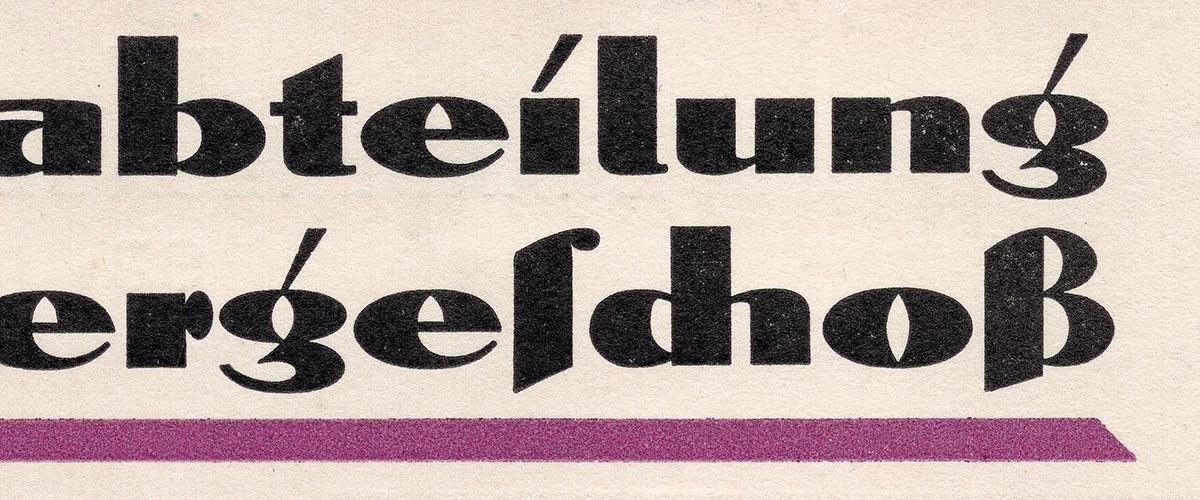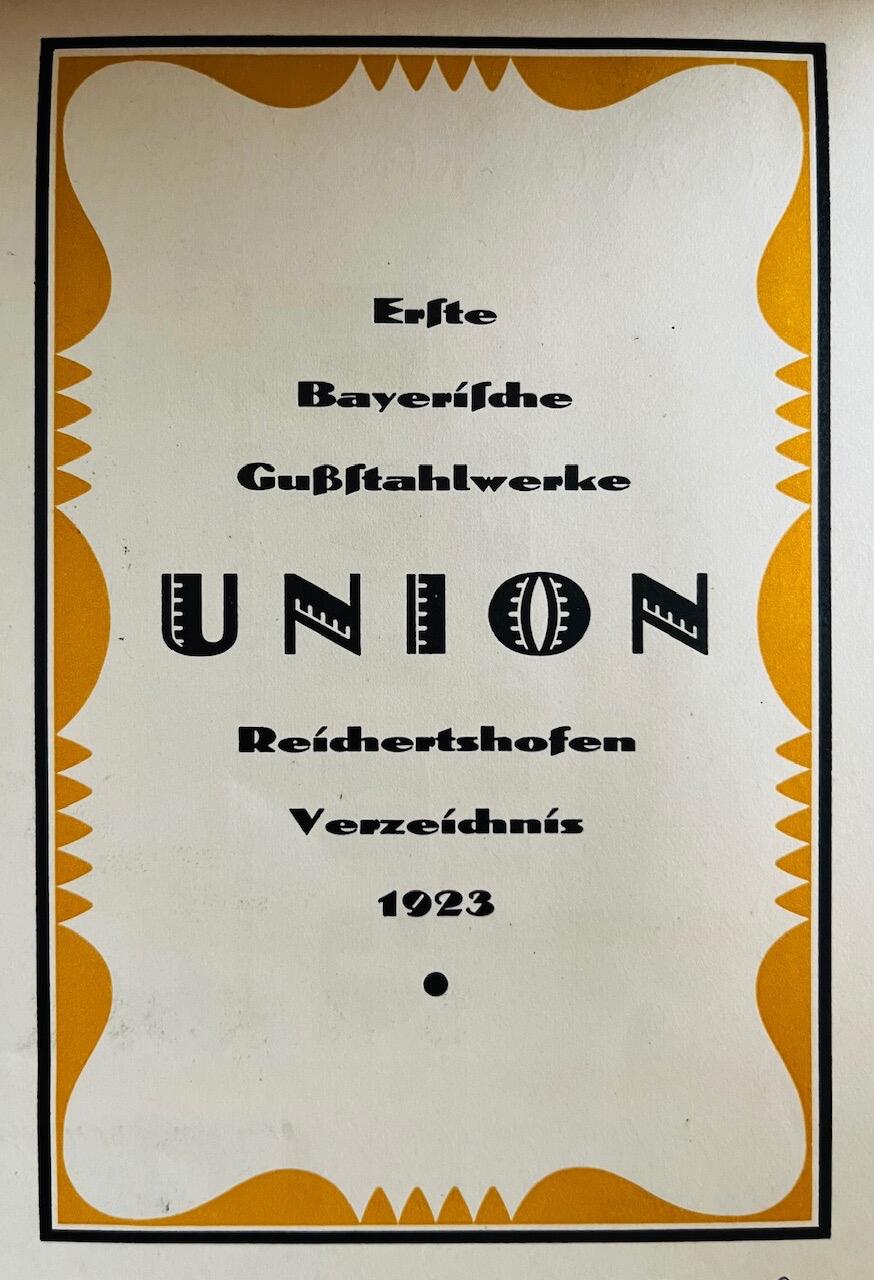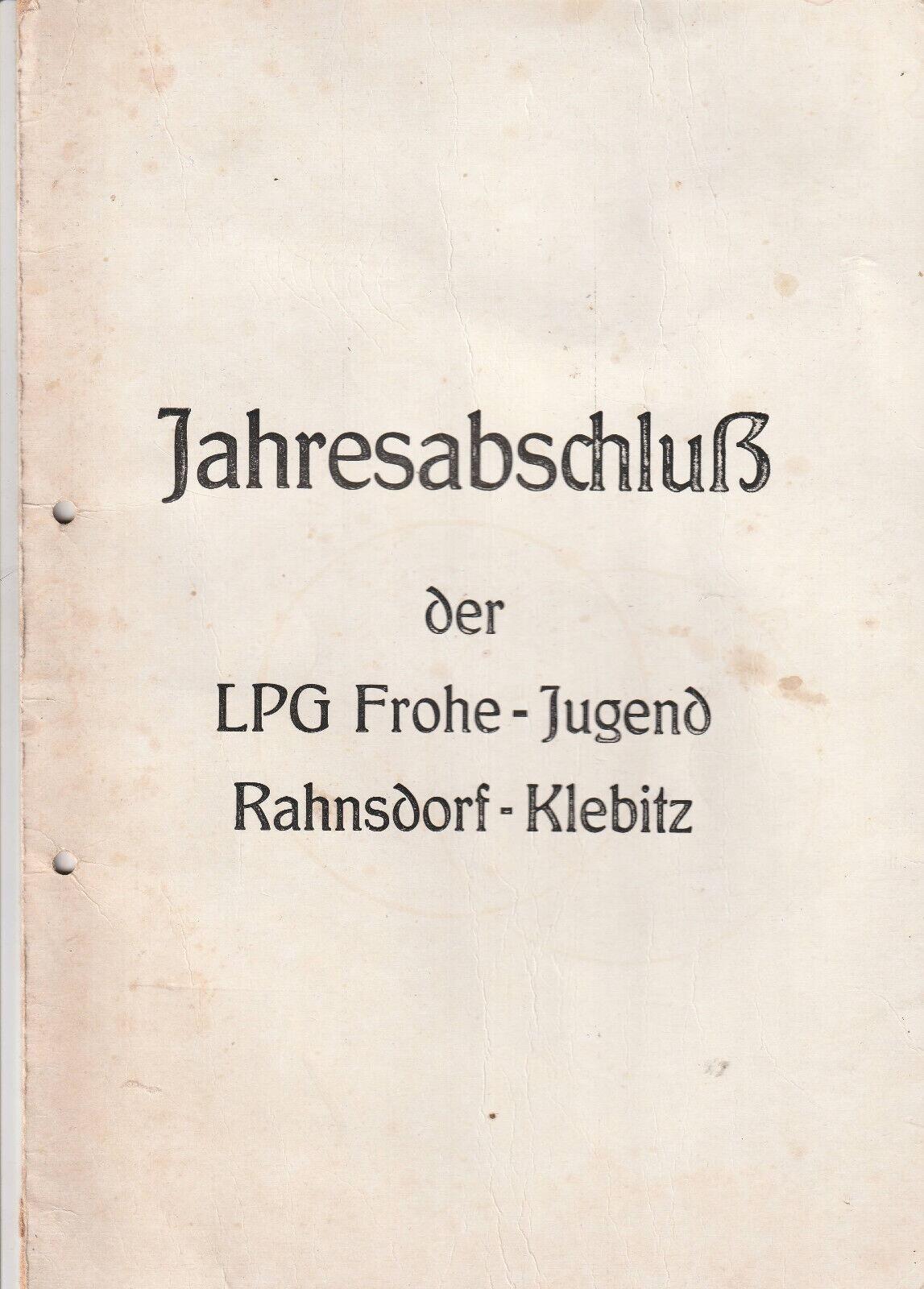
Eszett-Scans gesucht
Ich hab mir mal die Mühe gemacht, zu allen historischen Schriften mit ẞ gute Scans zu suchen oder anzufertigen und für jede Schriftfamilie zumindest ein ß und ein ẞ aus dem gleichen Schnitt zu digitalisieren. Das Ergebnis gibt es jetzt hier:
Um es aber absolut perfekt zu machen:
1.) Nicht finden konnte ich das ẞ für die Parcival von Thannhaeuser, die bei Wikipedia mit gelistet wird: https://de.wikipedia.org/wiki/Großes_ß#Historische_Schriften
Hat sie wirklich eins oder ist das womöglich ein Fehler in der Liste? Als Quelle wird ein Klingspor-PDF verlinkt. Dort sehe ich es aber nicht und auch nicht in dem Muster Antiqua-Schriften von Schelter & Giesecke, wo das ẞ vielfach, aber nicht für die Parcival verwendet wird.
2.) In der Wikipedia-Liste fehlt aktuell noch die Dolmen. Das große Eszett habe ich digitalisiert aber vom kleinen habe ich kein verwertbares Muster gefunden. Hat jemand eins und könnte es superhochauflösend scannen (1200 DPI aufwärts), damit ich es perfekt digitalisieren kann?
Ich kann dir das kleine Eszett aus der Einzelprobe scannen.
Wohl eher »danebengegriffen«. Die großen Schriftgrade sind ja einen Steckschriftkasten ohne Fächer für jeden Buchstaben. Da muss man außerhalb von A–Z und a–z einfach suchen. Wenn man da kein Profi ist und/oder das große Eszett gar nicht kennt, dann konnte man leicht glauben, an der richtigen Stelle zu sein. Die Form passt ja, nur die Proportionen nicht.
Aber wenn man will, kann man es auch als Absicht verkaufen. Vorn und hinten betont wie bei einem Rockband-Logo. ;-)